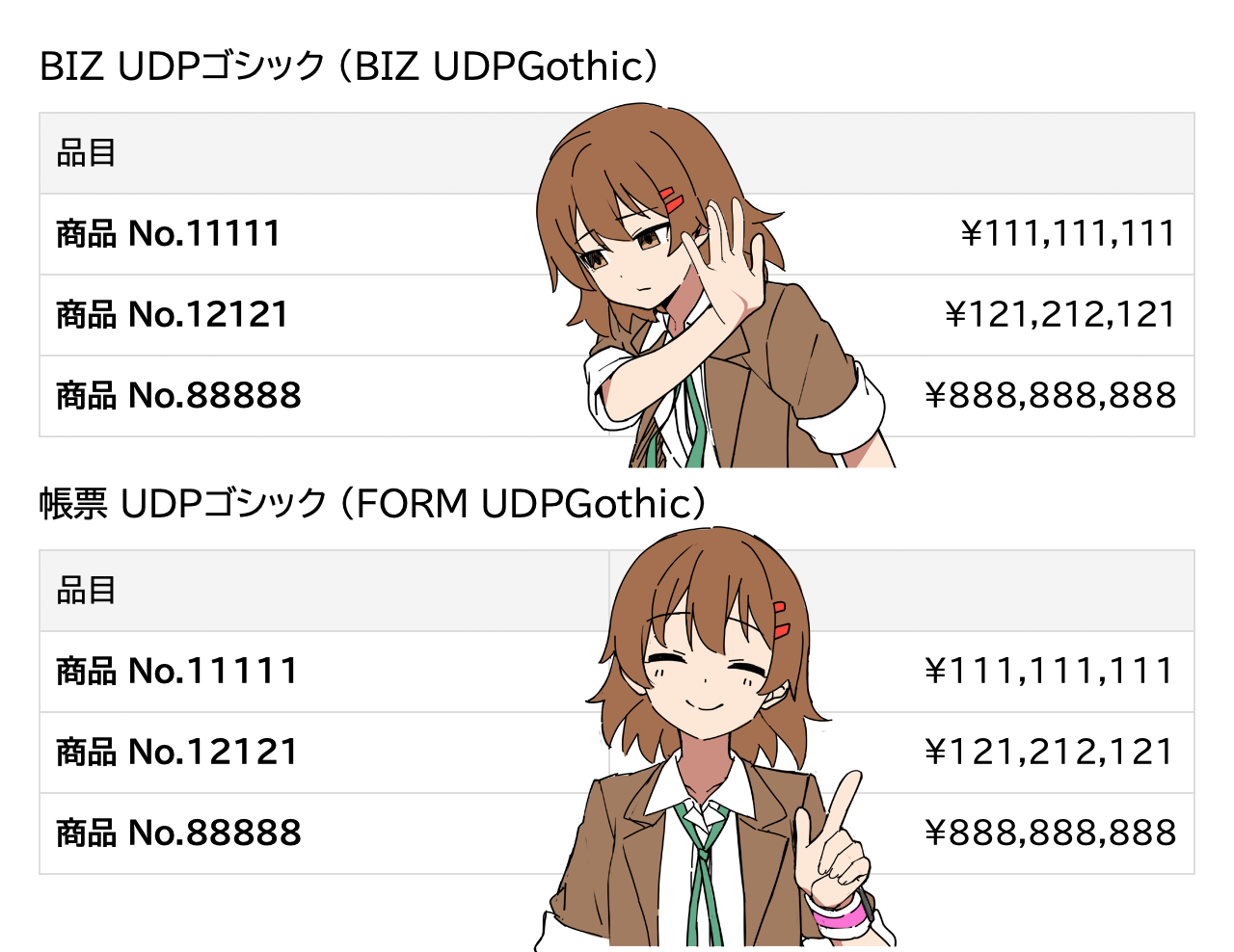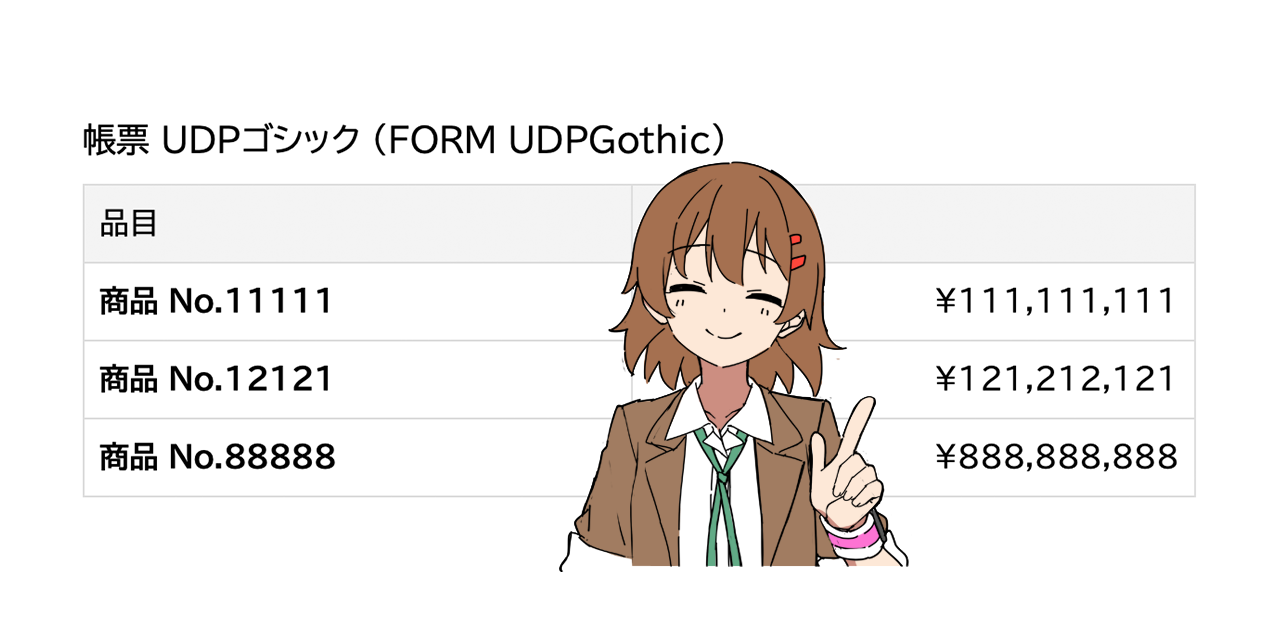
「BIZ UDPゴシック」の数字は、0〜9 のうち 1 のみ幅(サイドベアリング)が異なるので、1 のサイドベアリングを変更しています。「BIZ UDPゴシック」のグリフ数 13,932個のうち2個を変更し、残りの約 99.9856% のグリフは全く同じです。
帳票 UDPゴシック
モリサワ「BIZ UDPゴシック」の「1」と「1(全角)」の幅のみを変更し、数字(0〜9)を等幅にしたフォント「帳票 UDPゴシック (FORM UDPGothic)」です。
「BIZ UDPゴシック」を使いたい! でも、数字は等幅にしたい。でも、等幅の「BIZ UDゴシック」の数字は細すぎる! というときに使えるフォントです。
Windows の BIZ UDPゴシックとの違い
「帳票 UDPゴシック」は、オープンソースライセンスの「BIZ UDPゴシック(version 1.051)」を改変したフォントです(Google Fonts でも提供されているフォントです)。
Windows で提供されている「BIZ UDPゴシック(version 2.01)」と、「BIZ UDPゴシック(version 1.051)」は、グリフの形状はほぼ同じようですが、パラメーター等に多数の差異があり、少なくとも Windows 10 でレンダリング結果が異なる場合があります。
そのため、「帳票 UDPゴシック」も、Windows の「BIZ UDPゴシック」とは、レンダリング結果が異なる場合があります。